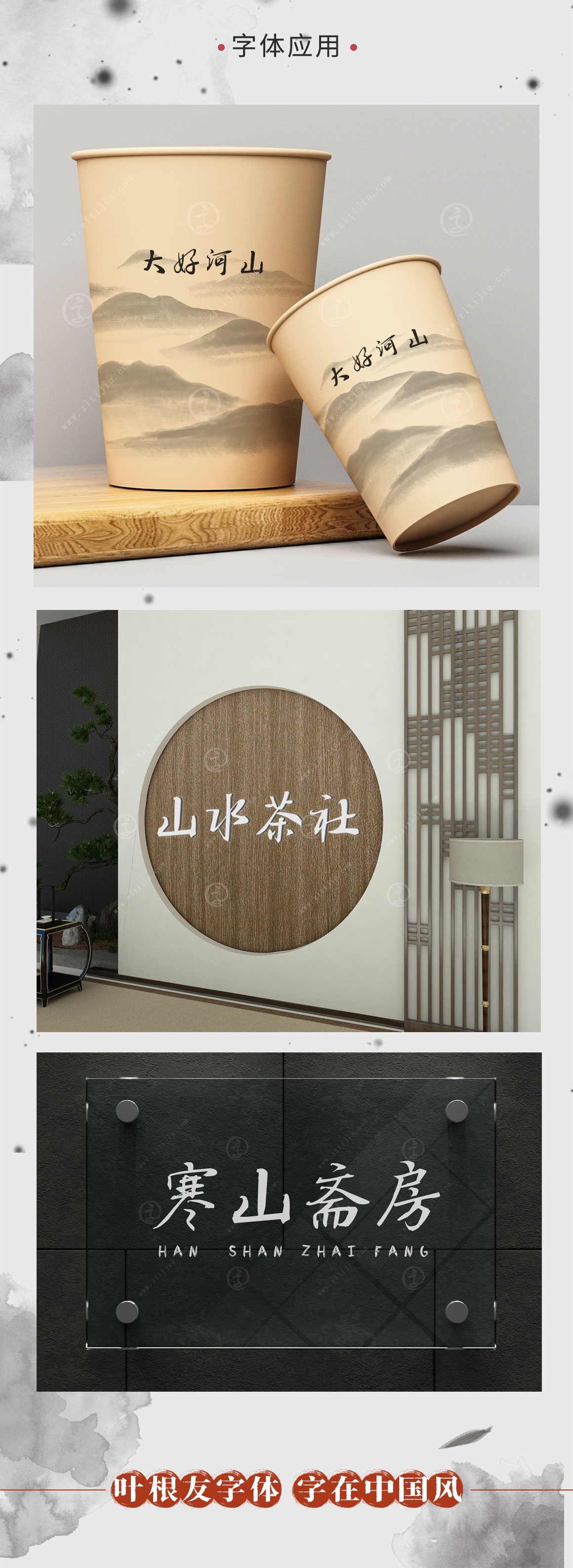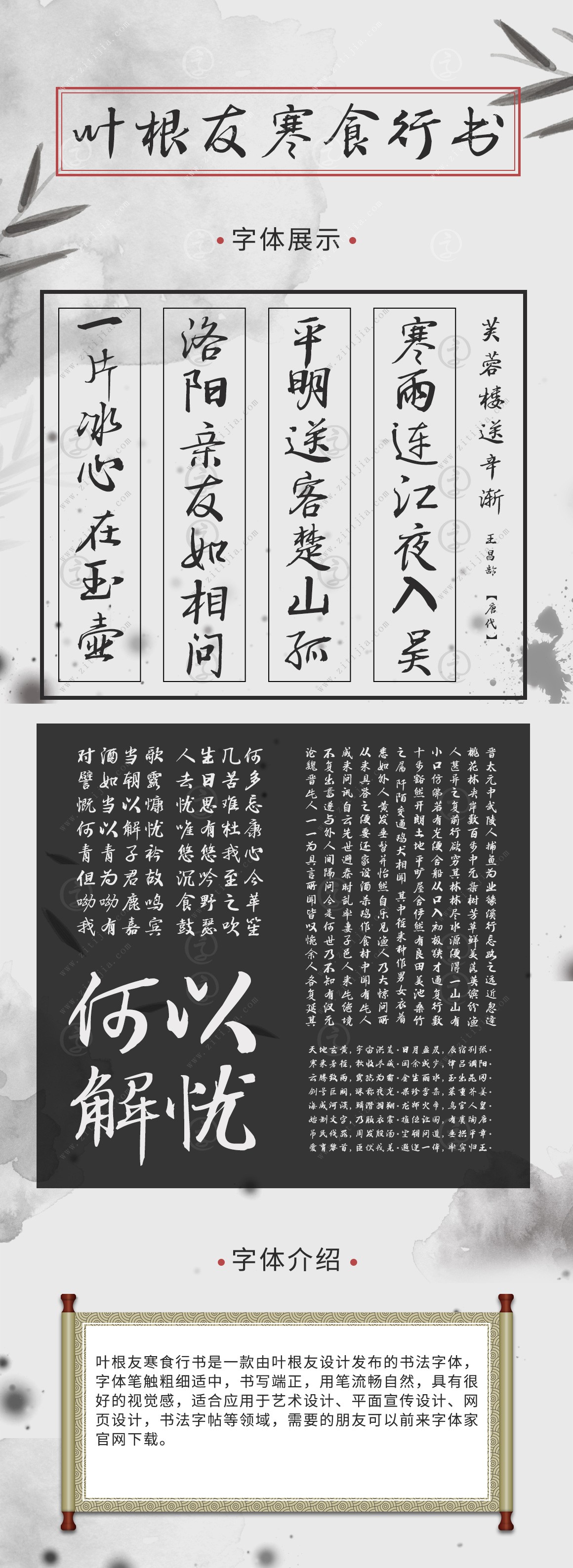
葉根友寒食行書是一款由葉根友設(shè)計(jì)發(fā)布的書法字體,字體筆觸粗細(xì)適中,書寫端正,用筆流暢自然,具有很好的視覺感,適合應(yīng)用于藝術(shù)設(shè)計(jì)、平面宣傳設(shè)計(jì)、網(wǎng)頁(yè)設(shè)計(jì),書法字帖等領(lǐng)域,需要的朋友可以前來下載。